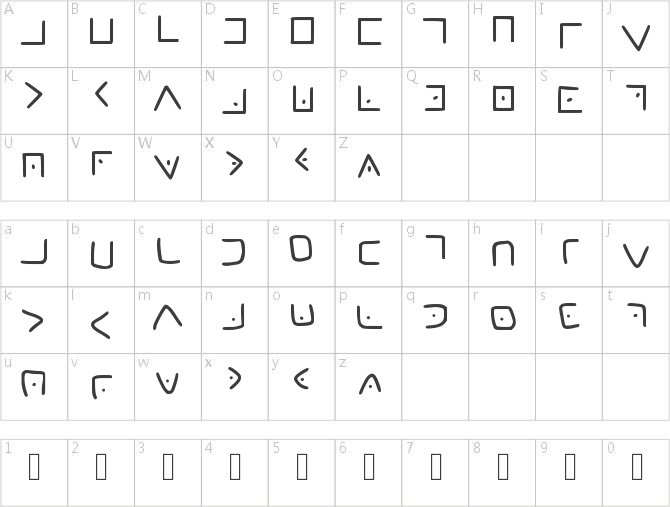
字體名稱: Masonic
Masonic-Cipher
Masonic-Cipher字體字庫(kù)是一款讓人賞心悅目、百看不厭的英文字體,適合各類廣告和產(chǎn)品包裝設(shè)計(jì)應(yīng)用,字體大小0.01MB,格式為ttf字體,上傳用戶是15331803325,作者/版權(quán)方為未知